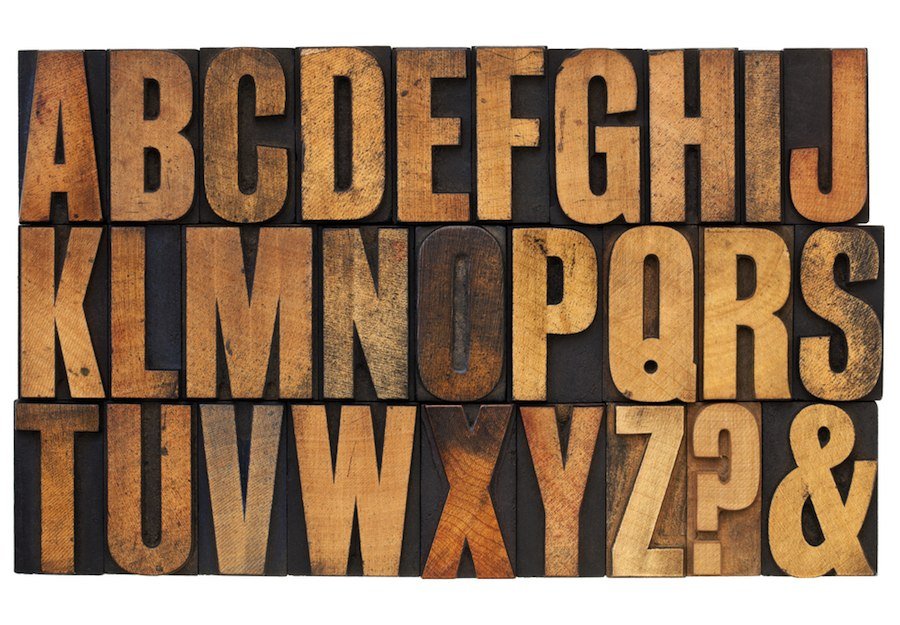
«La mejor tipografía es aquella que es invisible»
Para Lucinda Morrissey, profesora de la Facultad de Artes y Comunicación en la Universidad Europea, una tipografía es «el arte de organizar las fuentes para hacer un lenguaje visible, capaz de envolvernos en multitud de formatos y transmitir todos los mensajes necesarios para nuestra compleja vida moderna». Justo sobre esta materia imparte clase en el Grado de Diseño de la Universidad Europea.
De origen británico, está graduada por la Central Saint Martins de Londres, donde también estudió el tipógrafo Eric Gill, diseñador de la fuente Gill Sans en 1930, vive y trabaja en Madrid desde 1991.
P. ¿Para qué sirve una tipografía? ¿Cómo nos influye?
Según el poeta canadiense, tipógrafo y autor Robert Bringhurst, «la tipografía tiene al menos dos tipos de sentido… visual e histórico. La parte visual de la tipografía está siempre visible y los materiales para su estudio son muchos y están muy difundidos. La historia de los diseños de letras y de su uso también es visible para los que tienen acceso a manuscritos, inscripciones y libros antiguos, pero para los demás está oculta en gran parte…»
P. ¿Cuántas familias tipográficas existen?
Las fuentes del siglo XV se han diseñado, copiado y rediseñado hasta alcanzar la gran cantidad de fuentes disponibles en la actualidad. La clasificación más sencilla sería serif y sans serif, pero obviamente existen muchas otras posibilidades (cronológicamente, por atributos formales, influencias, sistemas, etc.).
P.¿Cómo se diseña una tipografía? ¿Qué aspectos se tienen en cuenta?
Inicialmente las tipografías fueron diseñadas y realizadas por grabadores e impresores, las primeras fuentes fueron una continuación de los manuscritos de los escribas. El diseño de una fuente requiere prestar mucha atención a detalles intrincados que más tarde no se percibirán, por ejemplo, para garantizar que ciertas combinaciones de letras (fi, ff, fl, etc) no choquen se incluyen ligaduras. El diseño de cada carácter requiere un gran control de los muchos atributos que componen la forma de una letra. En primer lugar se diseñan los caracteres clave (letras, números o símbolos) y el resto se crean utilizando los atributos establecidos con muchos pequeños retoques. De hecho, diseñar una verdadera buena fuente puede llevar mucho tiempo.
P.¿Cuál es el criterio a la hora de elegir una tipografía u otra? ¿Qué tipografía es la más adecuada para un currículo, para una tarjeta de presentación, para una invitación de un cumpleaños o boda, para un informe laboral…?
Hay fuentes diseñadas para situaciones específicas. Un buen diseñador debe ser consciente de sutilezas como que la sans serif es más legible en la distancia y en formato digital, pero demasiado mecánica para leer cómodamente un libro, para el que se prefiere la serif; o que hay otras fuentes más flexibles. Una fuente tiene que estar completa y tener todos los caracteres, números y símbolos necesarios para un trabajo, hay que tener cuidado porque muchas fuentes gratuitas están incompletas. Por último, cada tipo de letra tiene una personalidad que puede ser seria, frívola, de referencia histórica, decorativo… ¡Un mundo complejo y fascinante donde florecen los geeks de la tipografía!
P.¿Cuándo una tipografía tiene éxito?
Una fuente se convierte en un éxito cuando cumple con lo que se requiere de ella, pero esto es más fácil decirlo que hacerlo. La tipografía a menudo pasa inadvertida pero, curiosamente, la mejor tipografía es aquella que es invisible, tan apropiada para el trabajo que pasa desapercibida.